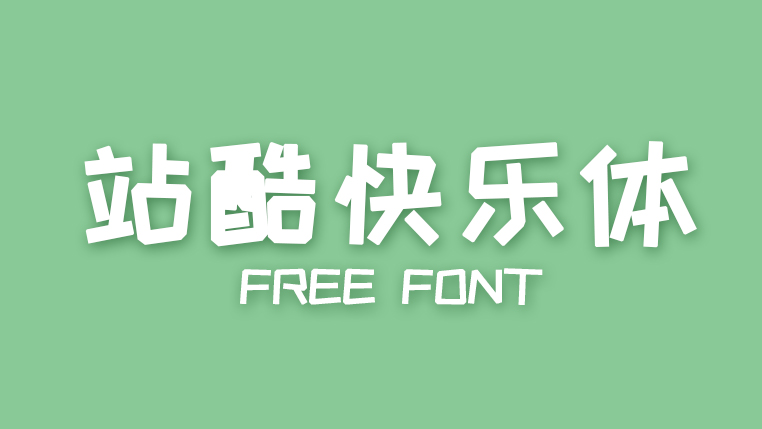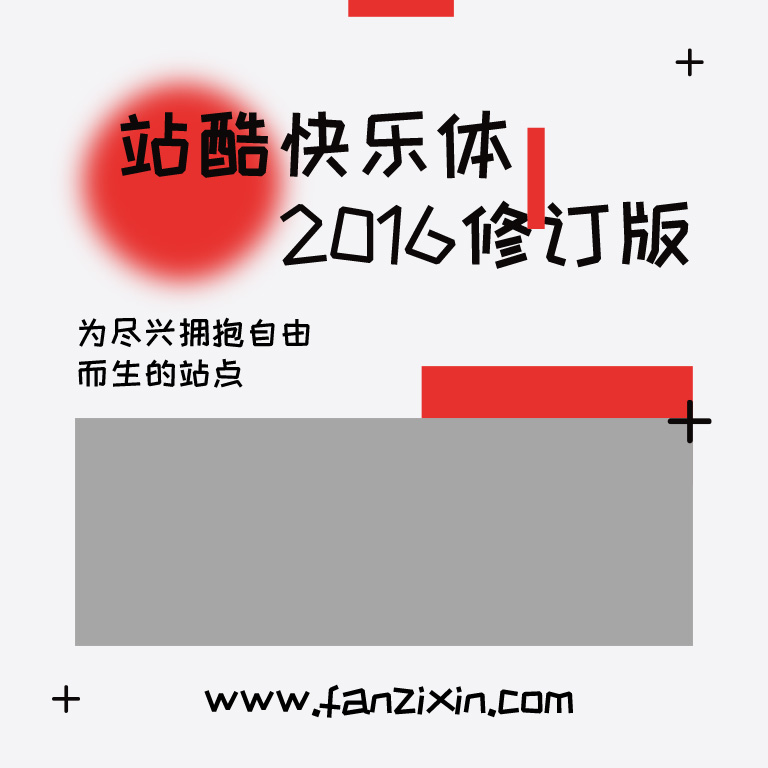
想要一笔一画都透着「快乐」的字体?站酷快乐体就是为欢快场景而生的。
字体介绍
站酷快乐体(ZCOOL KuaiLe)由站酷联合字体设计师刘兵克团队打造,是站酷免费商用字体家族中人气颇高的一款。
它笔画随性、节奏明快,天然带有手写的温度感,是节日与活动场景的常用字体。
字形特点
- 活泼俏皮:笔画带有手写笔触的随意感,字形跳动有节奏,快乐氛围直接拉满。
- 亲和力强:没有工业字体的冷硬感,天然适合需要温暖、亲切表达的场景。
- 识别度高:标题与大字号下辨识度突出,用在促销、节日海报上格外醒目。
字重与字数
- 单字重设计,以手写标题形态呈现。
- 覆盖常用简体中文字符,适合标题与短文案。
字体使用建议
这款字体在以下场景表现尤其出色:
- 节日与活动海报
- 儿童与亲子主题
- 促销 Banner 与价签
- 社交媒体配图